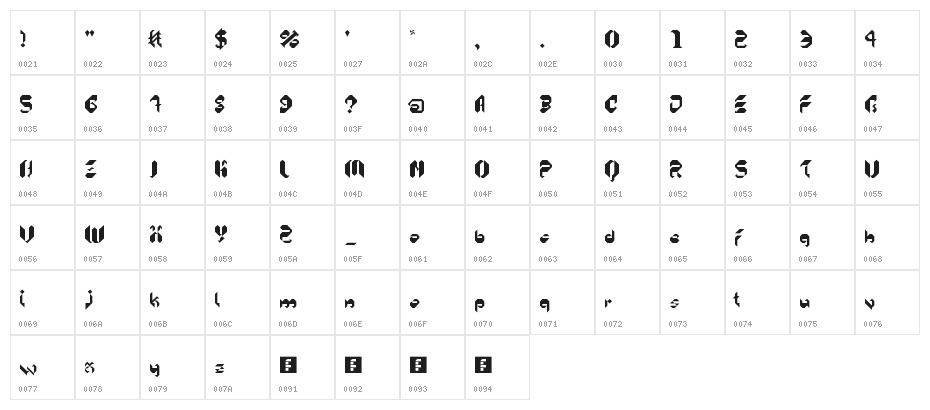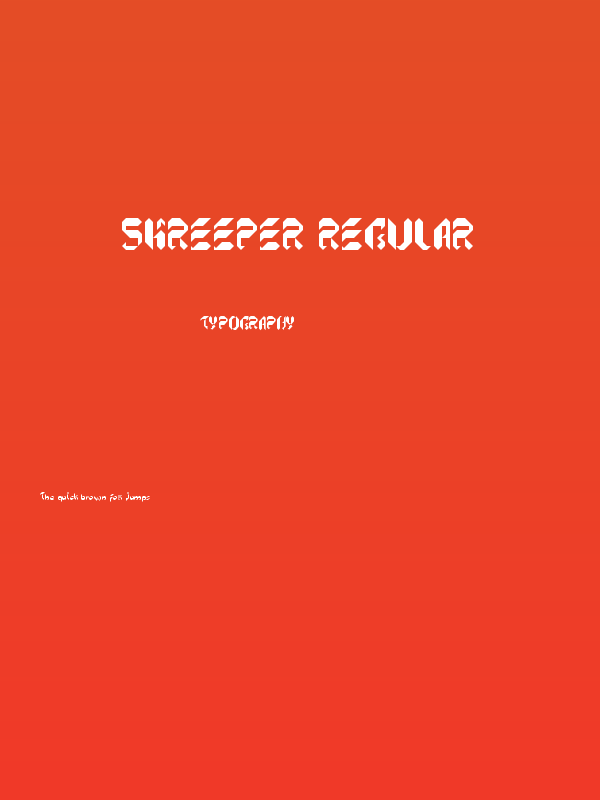
5Kreeper Regular Font
| Progetti proposti | Ideal for sci-fi themed designs, video game titles, posters, and branding that seeks a modern, edgy feel. |